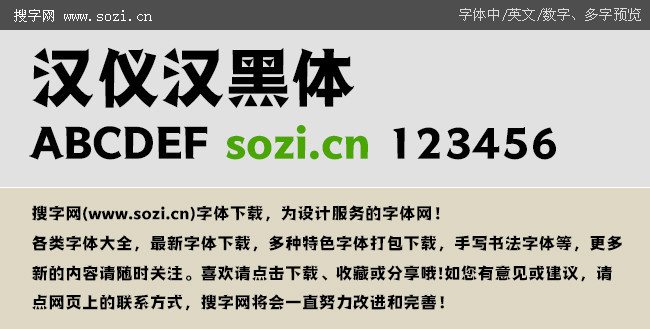
漢儀漢黑體
搜字網(wǎng)提供一款漢儀漢黑體中文字體下載,漢儀漢黑體將中國漢隸的筆法與黑體相互融合,形成一種大方、穩(wěn)重且富有歷史韻味的黑體。整套字體古樸渾厚,拙中帶巧,筆畫與字形間透露著爨書的古雅和內(nèi)剛外柔的特點(diǎn)。適合標(biāo)題設(shè)計(jì)、畫冊設(shè)計(jì)、海報(bào)設(shè)計(jì)等場合使用。(本字體為個(gè)人非商用版,如需要商用請聯(lián)系漢儀公司購買版權(quán))